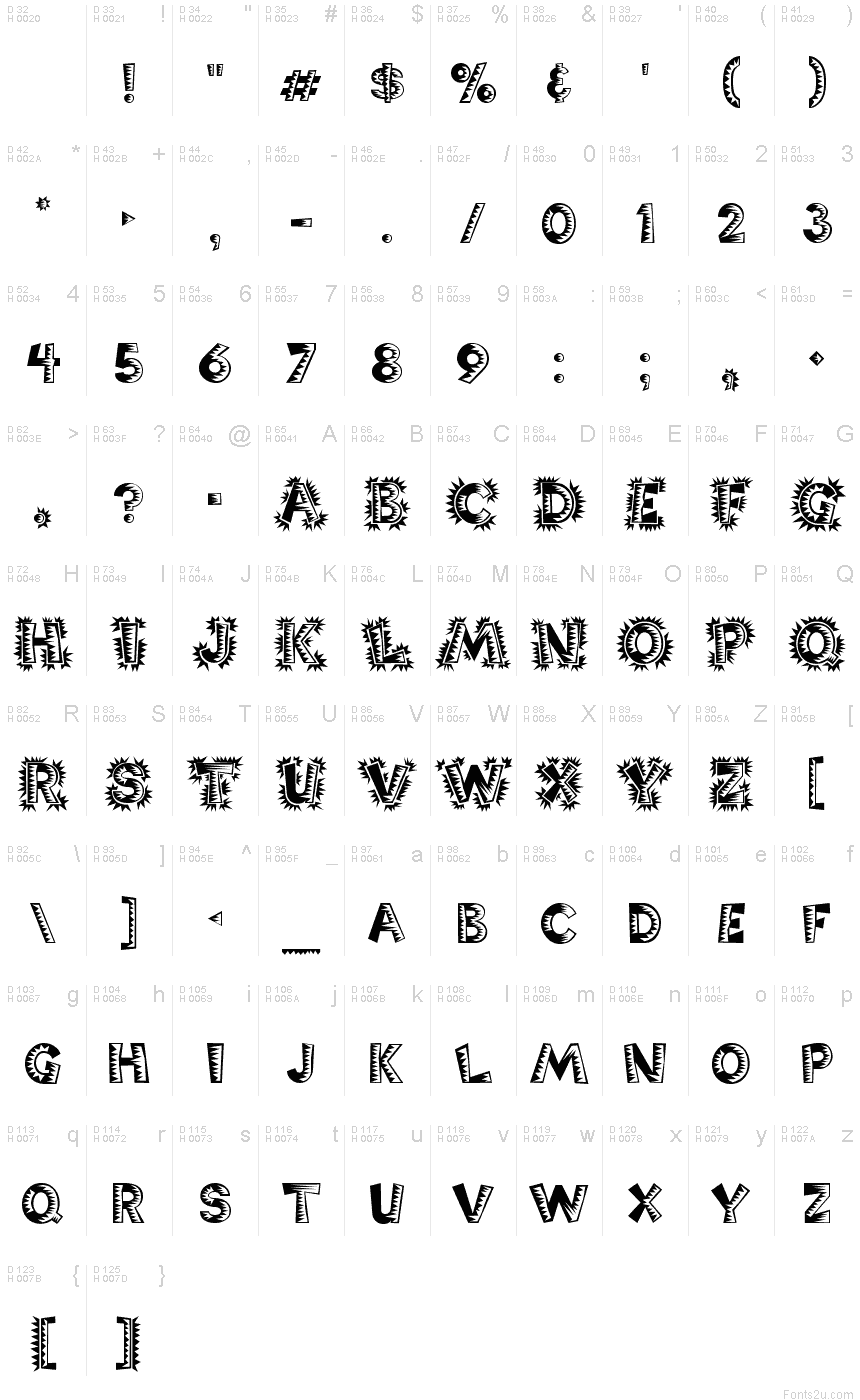
Poptics One, darmowy font display od Patricii Lillie z 1993 roku, zmienia alfabet w eksplozję czarnych kształtów, ząbkowanych wycięć i gwieździstych promieni. Litery są wyraziste i zabawne, a ich masywne formy, poprzecinane zygzakami i ostrymi obwódkami, nadają projektowi energię rodem z plakatów komiksowych.
Sprawdzi się wszędzie tam, gdzie liternictwo ma działać jak grafika – ulotki na imprezy, okładki zinów, plakaty klubowe w stylu retro, nietypowe opakowania czy plansze tytułowe to idealne zastosowania dla tego darmowego fontu. Wykorzystaj go do krótkich nagłówków, szkiców logo czy inicjałów, gdy chcesz, aby same litery niosły ze sobą dynamikę i wyrazisty charakter.